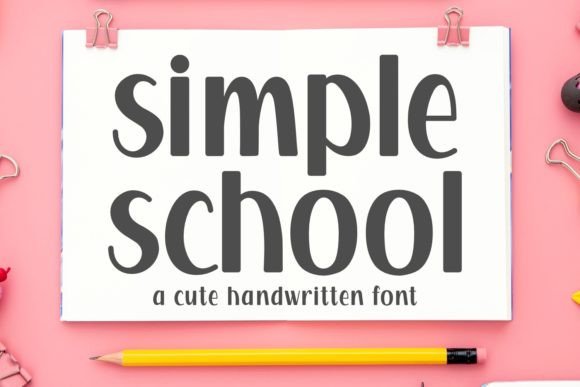
Simple School
適切なデザイン要素を見つけるのは難しい場合がありますが、Simple Schoolは作品を即座に引き立てる優れたコレクションを提供します。
精密に作られたSimple Schoolは、クリーンなベクター、滑らかなタイポグラフィ、そして安心のための商用ライセンスを提供します。
POD(オンデマンド印刷)製品、結婚式の招待状、またはソーシャルメディアのグラフィックを作成している場合でも、Simple Schoolは理想的です。